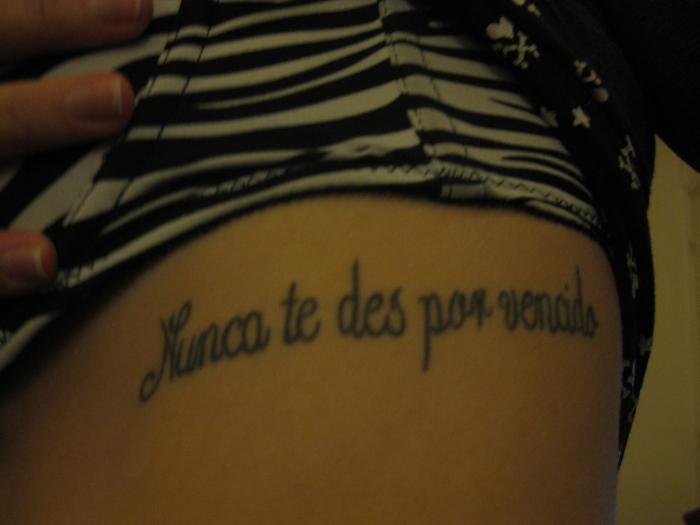
Suche super dringend nach dem Namen dieser Schrift!
ich suche ganz dringend nach dem Namen dieser Schriftart. Es wäre super, wenn irgendjemand das vielleicht rausfinden könnte... Bin schon sehr lange auf der Suche danach und habe bisher über Schriftarten-Generatoren nur so ähnliche Schriftarten, aber nicht hundertprozentig dieselbe gefunden :(
Das wird wohl daran liegen, daß das wahrscheinlich handgemacht ist und man deshalb nur ähnliche Schriften finden kann.
Nur noch mal so zum Verständnis: Du hast eine Tätowierung auf dem seitlichen Brustkorb, deren Schriftart Dich schon ganz lange brennend interessiert und die auf deutsch so viel wie "Niemals aufgeben" heisst.
Das kann man so sagen, ja :D Bin natürlich schon selbst auf die Idee gekommen, einfach nochmal eben zum Tattoostudio zu gehen und nachzufragen, welche Schriftart das war... Das Problem ist aber, dass dieses Studio am anderen Ende der Welt liegt, ich dort so schnell nicht wieder hinkomme und alle Anfragen per Mail oder Telefon oder sonst was bisher ohne Antwort blieben, was evtl. daran liegen mag, dass dieses Studio umgezogen ist usw.
Wofür musst du 100%ig diese Schrift haben? Willst du ein neues Tattop machen lassen, das dazu passt? Das sollte man eigentlich nach den vorhandenen Buchstaben nachempfinden können und die evtl. fehlenden Zeichen dazu erfinden ...
Das kann man so sagen, ja :D Bin natürlich schon selbst auf die Idee gekommen, einfach nochmal eben zum Tattoostudio zu gehen und nachzufragen, welche Schriftart das war... Das Problem ist aber, dass dieses Studio am anderen Ende der Welt liegt, ich dort so schnell nicht wieder hinkomme und alle Anfragen per Mail oder Telefon oder sonst was bisher ohne Antwort blieben, was evtl. daran liegen mag, dass dieses Studio umgezogen ist usw.
Ich wundere mich eigentlich, dass man bei allem, dass ein Schriftzug ist, immer und ausschließlich davon ausgeht, dass dahinter auch ein Font steht (auch wenn ich schon 2 Fotos zu gesendet bekommen habe, indem eine meiner Schriften für ein Tattoo verwendet wurde. Gerade gute Schrift-Tätowierer sind auch oft Kalligrafen, deren persönliche Ehre es erfordert, einen Schriftzug in einem, zum Text und der tätowierten Stelle mit den dortigen Formen passend frei zu zeichnen. Nicht selten wird eher umgekehrt ein Schuh draus, indem mämlich viele größen der Schrift-Gestalter-Zunft ihre Schriftarten nach den Werken unbekannter Steinmetze, Kupferstecher, Schildermaler erstellen, oder kalligrafische Handschriften präzisieren und um fehlende Glyphen ergänzen.
Bis zum Aufkommen von Letraset-Transfer-Blättern mitte der 1970er Jahre waren eigentlich alle Schriftanwendungen außerhalb im Buchdruck erstellter Drucksachen von Hand gezeichnet, und das betraf eigentlich alle Logos, zumal die Zahl der verfügbaren Schriftarten beim Drucker des Vertrauens damals doch sehr überschaubar war, da hatte selbst die Version 1.2 von CorelDWAW schon eine reichhaltigere Schriftenauswahl an Bord, auch wenn diese gerade einmal eine 1,4MB-Diskette umfasste.
Gerade gute Schrift-Tätowierer sind auch oft Kalligrafen, deren persönliche Ehre es erfordert, einen Schriftzug in einem, zum Text und der tätowierten Stelle mit den dortigen Formen passend frei zu zeichnen.
Das ist aber äußerst optimistisch ausgedrückt – das ist wenn mal einer unter tausenden, der das bewusst kann und ganz bestimmt nicht freihändig ...
Optimistisch? Ich sprach ja gerade von GUTEN Schrift-Tätowierern, also welche, die sich auf Schrift spezialisiert haben. Das die nicht in jeder Pieks-Bude zu finden sind, ist mir schon klar, dafür laufen viel zu viele mit entstellenden Kritzeleien unter der Haut herum.
Bis zum Aufkommen von Letraset-Transfer-Blättern mitte der 1970er Jahre waren eigentlich alle Schriftanwendungen außerhalb im Buchdruck erstellter Drucksachen von Hand gezeichnet
Abgesehen von den dry-transfer sheets von Letraset, Mecanorma und anderen Anbietern gab es ja auch noch die vielen verschiedenen Fotosatzsysteme womit man Überschriften setzen lassen konnte. Photolettering, VGC Phototypositor, ATF Hadego, Starsettograph, Berthold Starograph und Staromat, Letterphot, Dr. Böger Copytype, Stempel Typomatic usw. hatten alle Kataloge mit hunderte von (Headline-)Schriften. Teils handelte es sich hierbei um Kopien von bereits existierende Schriften (Buchdruck oder Vorlagen für Schildermaler usw.) aber auch sehr viele Neuschöpfungen. Viele Fotosatzsstudios boten auch Schriftmodifikation und Reinzeichnung als zusätzliche Dienstleistung an. In dieser Zeit sind wahrscheinlich sehr viele Logos so entstanden, dass der Art- oder Typedirector eine vorhandene Schrift nachskizzierte und die gewünschte Änderungen angab. Anschließend machte dann das Fotosatzstudio die Reinzeichnung. Oder die Agentur / der Designer bestellte die für ein Logo benötigten Buchstaben als Fotosatzfahne und nahm die Überarbeitung und Reinzeichnung selbst vor.
Albert-Jan Pool hat mit den vielen anderen Möglichkeiten und den anderen Marken solcher Transferschriften natürlich recht,
Mit der Nennung der einen Marke (Quasi als Begriffsmonopol, ich hätte mit Lokalpatriotismus ja auch „Typofix“ schreiben können) wollte ich ja nur den zeitlichen Rahmen setzen, indem es für Grafiker leichter wurde, Text-Logos zu gestalten.
Ob jetzt der Zeichner im Fotosatz-Studio saß oder eine Grafik-Agentur oder ein einzelner Designer/Grafiker jetzt nach einer Fotosatz- (oder sogar Bleisatz-) Fahne oder gar nur einem Schrift-Musterbuch oder -Kartei ein Logo entwarf, oder sich eben nur an die Formen einer Schrift erinnerte, oder sie gleich ganz entwarf ist in diesem Zusammenhang eigentlich egal. Die weitaus meisten Logos vor aufkommen der Computergrafik waren dann letztlich doch Handzeichnungen, die dann von der als Vorlage dienenden Schrift doch mehr oder weniger abwichen.